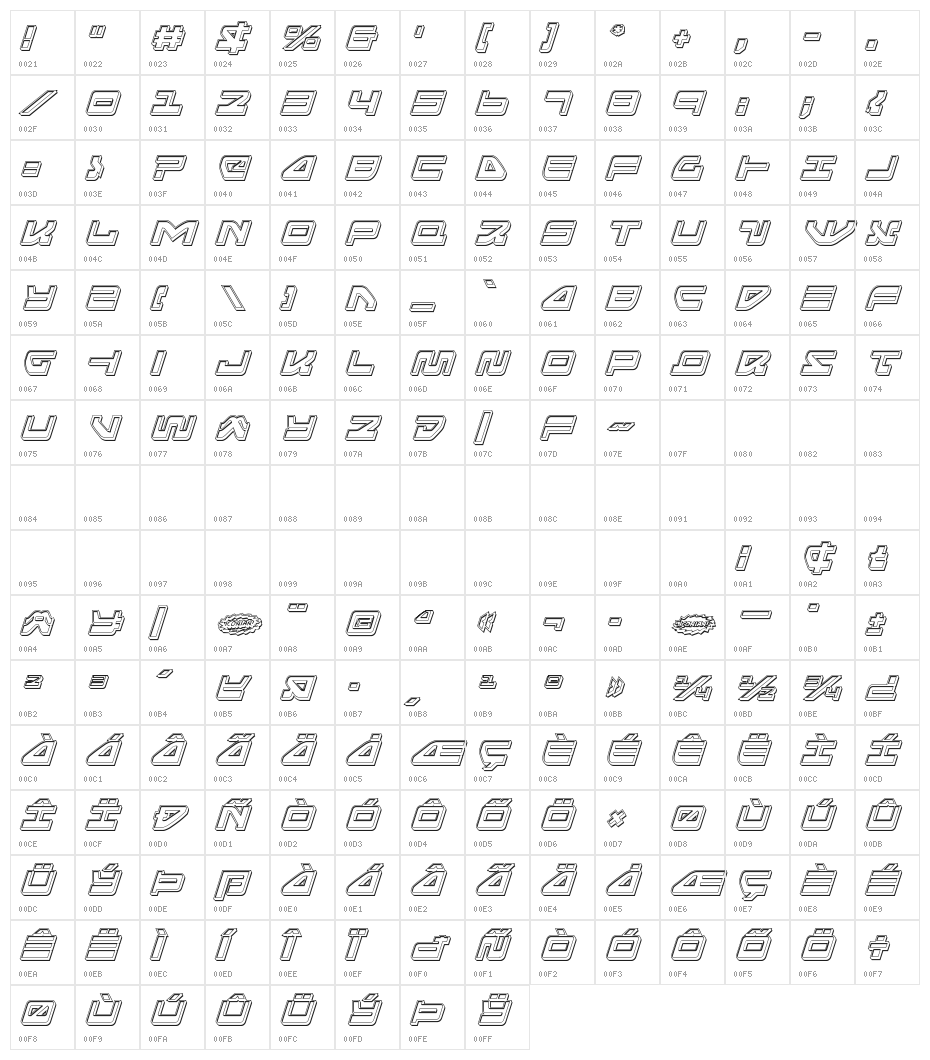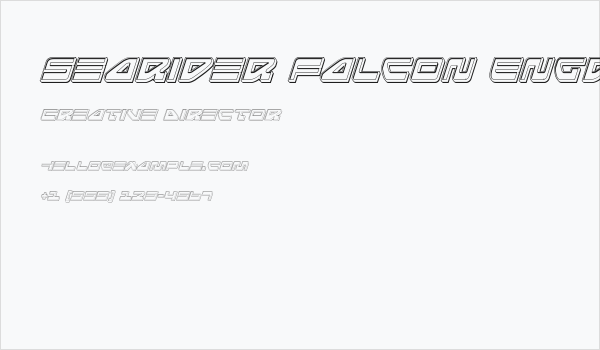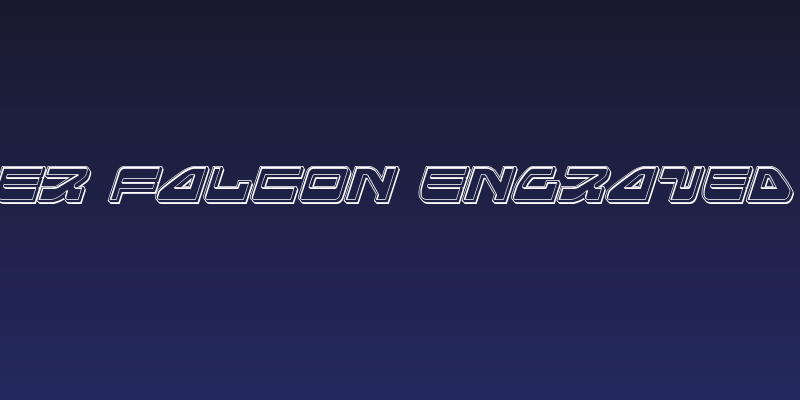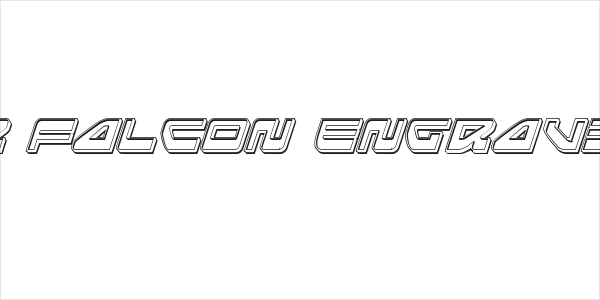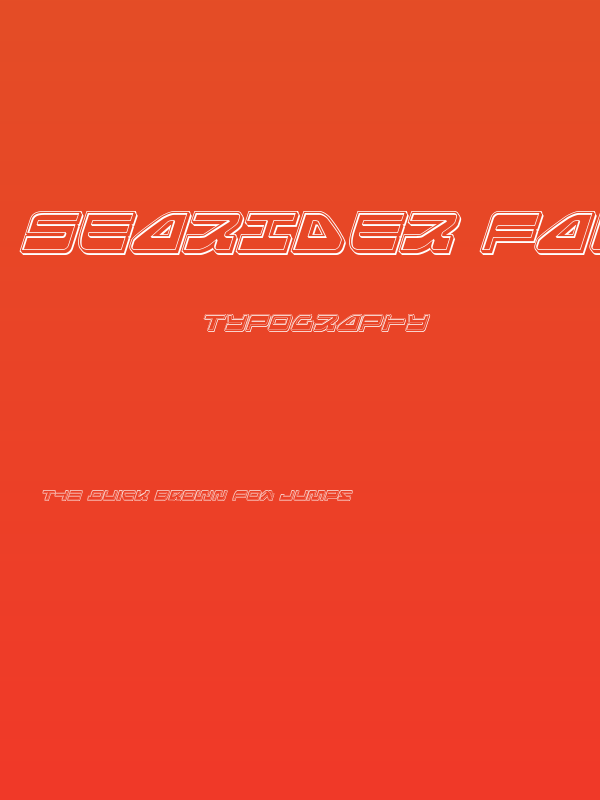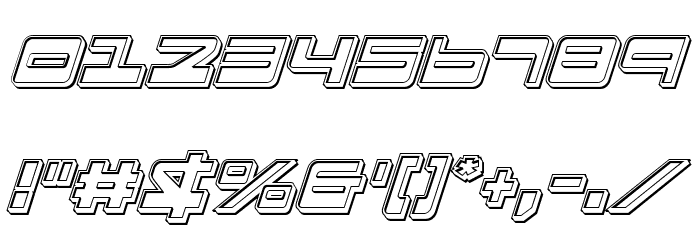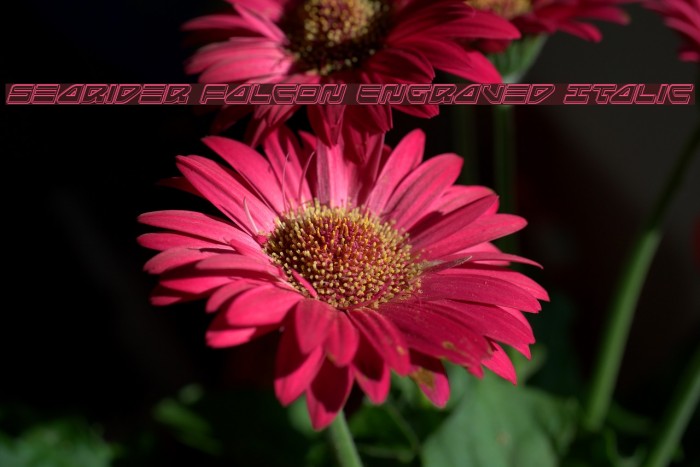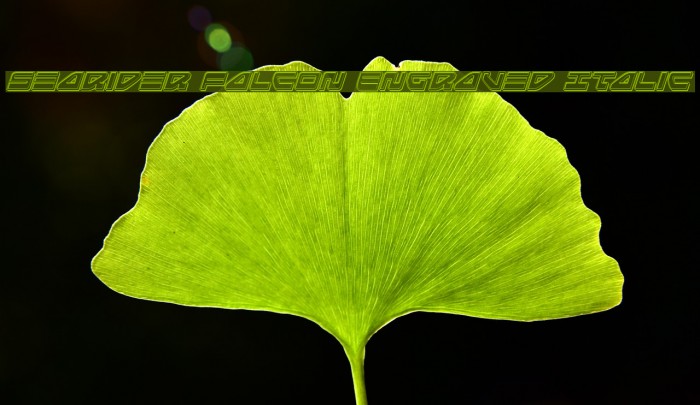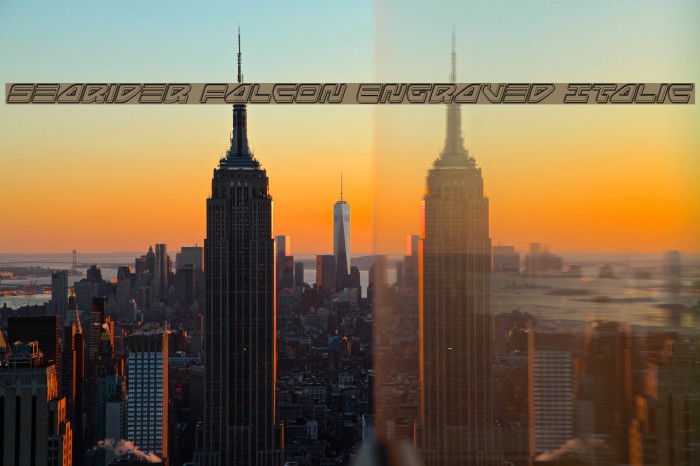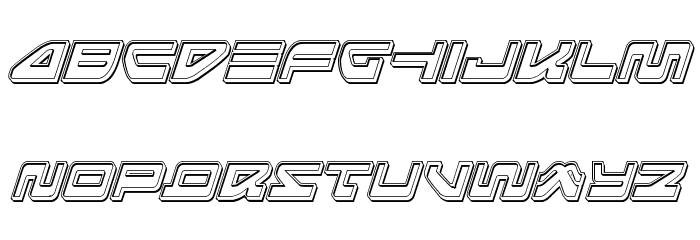
Searider Falcon Engraved Italic Font
| Estilo general | Futuristic, Modern |
| Proyectos propuestos | Ideal for sci-fi themed designs, video game titles, tech branding, and futuristic posters. |